싸인은 단순한 서명이 아니라, 나만의 개성과 스타일을 담아낼 수 있는 하나의 예술이에요. 서류를 작성할 때, 계약서에 서명할 때, 팬들에게 사인을 해줄 때, 멋진 싸인은 자신감을 심어주고 프로페셔널한 이미지를 만들어줘요. 하지만 기존 싸인이 너무 평범하거나 투박하게 느껴진다면? 지금부터 싸인을 세련되게 바꾸는 5단계 과정을 함께 살펴볼게요! 🖋️
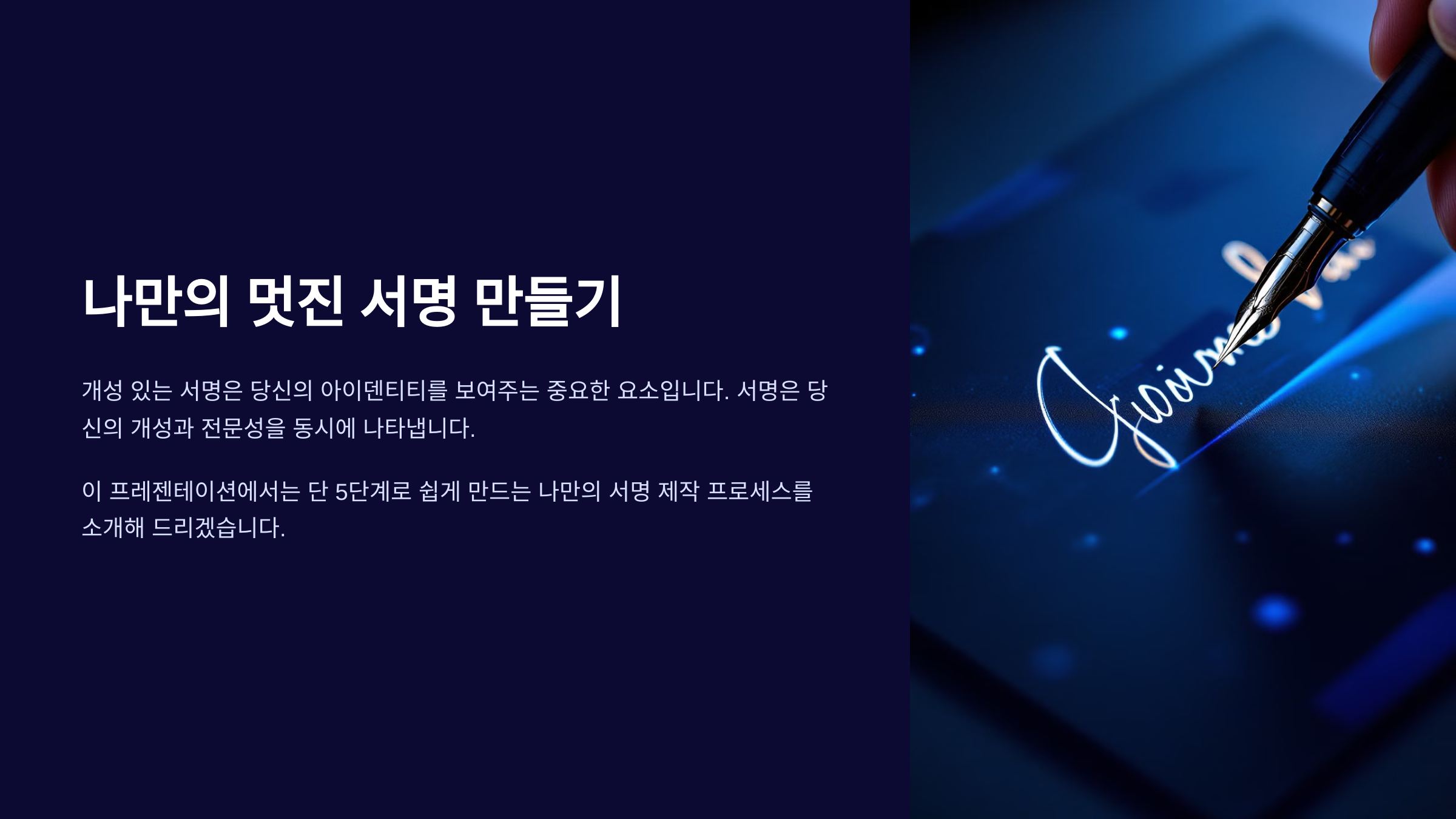
싸인을 바꾸는 과정은 단순한 글씨 연습이 아니라, 자신만의 개성과 스타일을 찾는 과정이기도 해요. 내가 생각했을 때, 싸인은 나를 표현하는 중요한 요소 중 하나예요. 그러니 단순히 멋있어 보이는 싸인을 따라 하기보다, 나에게 어울리는 싸인을 찾고 다듬는 것이 중요하답니다. 자, 이제 본격적으로 시작해 볼까요? ✨
1단계: 현재 싸인 분석하기 🔍
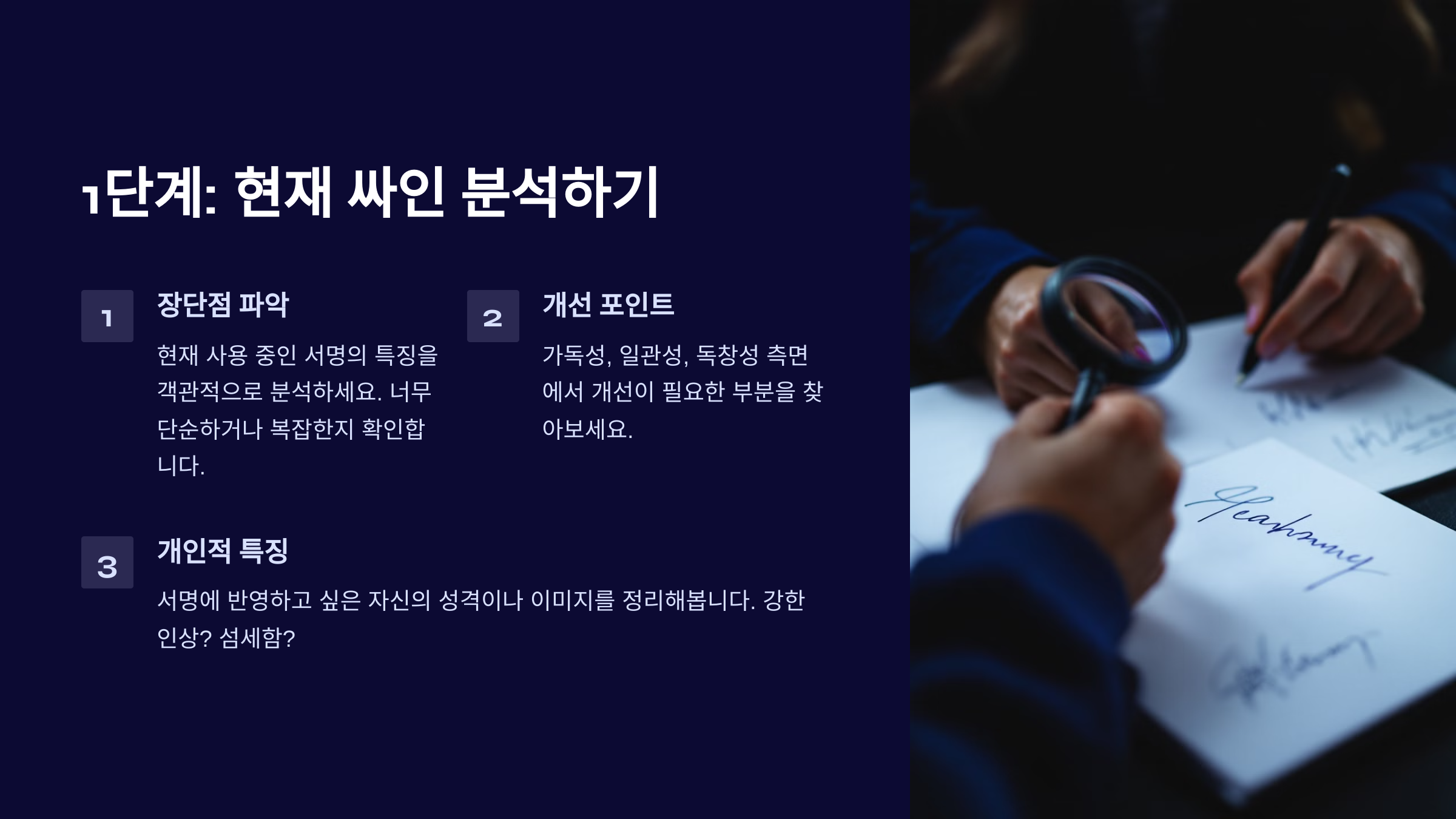
먼저, 현재 사용하고 있는 싸인을 분석하는 것이 중요해요. 어떤 점이 마음에 들고, 어떤 부분을 개선하고 싶은지 명확하게 파악하는 과정이 필요하죠. 싸인의 크기, 글자의 연결 방식, 가독성 등을 체크하면서 개선할 부분을 찾으면 좋아요. ✏️
📌 자신의 싸인을 분석하는 방법:
- 현재 싸인을 여러 번 써보고, 어떤 부분이 자연스럽고 어떤 부분이 어색한지 확인해요.
- 서명이 너무 크거나 작지는 않은지 체크해요.
- 읽기 쉬운 싸인인지, 아니면 너무 복잡한지 고민해봐요.
- 빠르게 쓸 때도 형태가 유지되는지 테스트해요.
✏️ 싸인의 주요 요소 분석 🧐
요소 분석 포인트 가독성 이름이 명확하게 보이는지? 연결 방식 글자들이 자연스럽게 연결되는지? 스타일 너무 평범하거나, 과하게 복잡하지 않은지? 속도 빠르게 써도 유지될 수 있는 디자인인지? 이렇게 싸인의 기본 요소를 점검한 후, 개선하고 싶은 포인트를 정리해요. 다음 단계에서는 어떤 스타일의 싸인이 나에게 잘 맞을지 찾아볼 거예요! 🔎
2단계: 원하는 스타일 찾기 🎨
이제 싸인을 더 세련되게 만들기 위해 나만의 스타일을 찾아야 해요. 싸인은 단순한 서명이 아니라, 개성과 감각을 담을 수 있는 작은 예술 작품이 될 수도 있답니다. 원하는 스타일을 찾기 위해 여러 가지 예시를 살펴보면서 자신의 이름과 조합해 보는 것이 중요해요. 🖊️
📌 대표적인 싸인 스타일 유형:
- 🖋️ 클래식 스타일: 정갈하고 읽기 쉬운 서명 (예: 정자체, 부드러운 곡선)
- ⚡ 모던 스타일: 빠르게 쓸 수 있도록 단순하면서도 감각적인 디자인
- ✨ 예술적 스타일: 독특한 필기체와 곡선을 강조한 서명
- 🔗 이니셜 스타일: 이름의 첫 글자만 강조해서 빠르고 강렬한 인상을 남김
📌 싸인 스타일 비교표 🖋️
스타일 특징 추천 대상 클래식 스타일 정갈하고 가독성이 좋은 서명 공식 문서, 계약서 서명에 적합 모던 스타일 단순하면서도 세련된 디자인 디자이너, 창작 활동을 하는 사람 예술적 스타일 곡선과 독특한 필기체 활용 예술가, 연예인, 크리에이터 이니셜 스타일 이름의 첫 글자만 강조 비즈니스 리더, 공인 자신의 이름을 여러 스타일로 써보면서 어떤 스타일이 가장 어울리는지 확인해 보세요. 싸인을 직접 연습하면서 자연스럽게 손에 익히는 것도 중요해요. 🎨
3단계: 기본 형태 디자인하기 ✏️
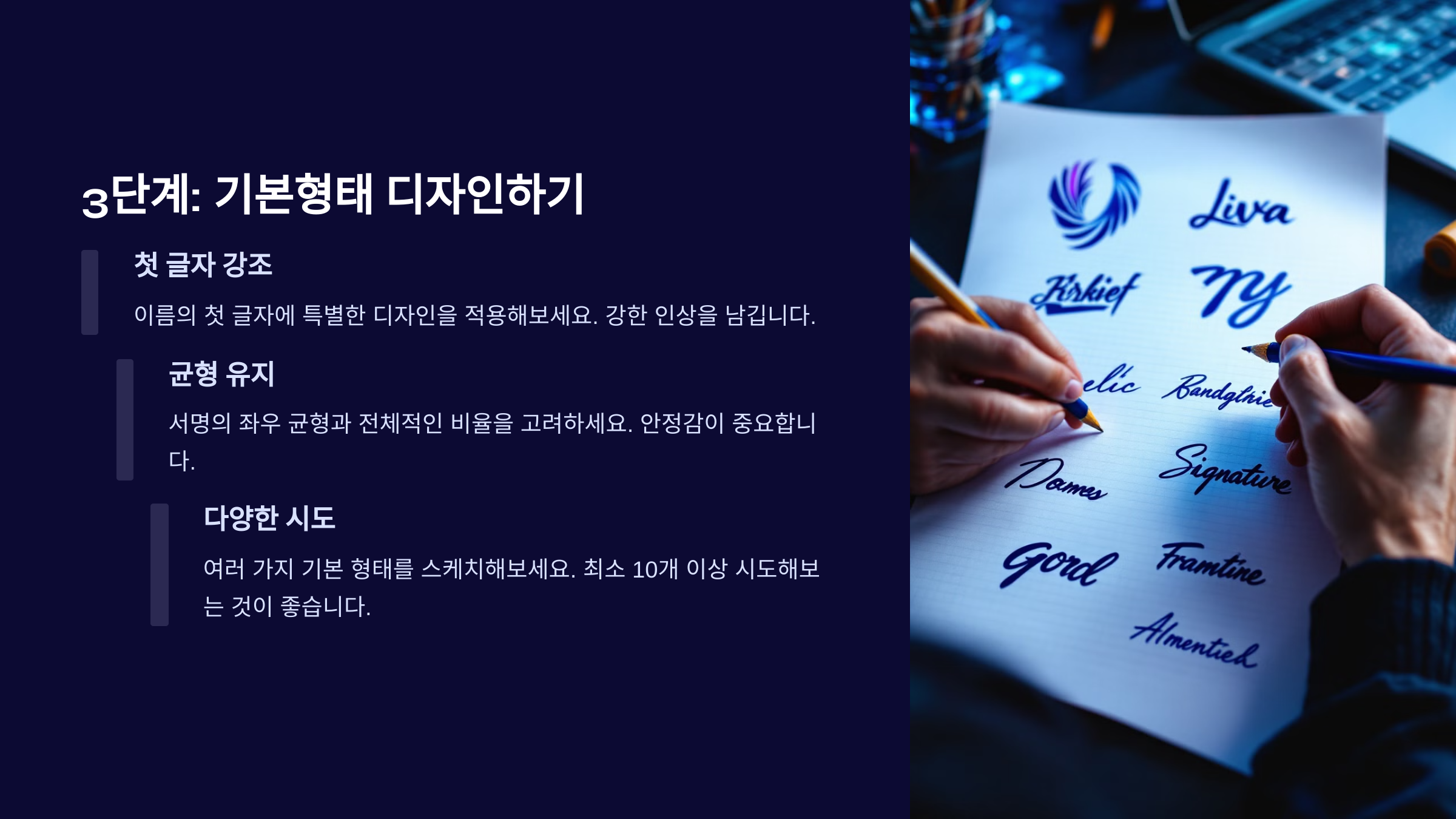
이제 원하는 스타일을 정했다면, 본격적으로 싸인의 기본 형태를 디자인할 차례예요. 싸인은 빠르게 쓰면서도 일관된 형태를 유지해야 하기 때문에, 단순하면서도 균형 잡힌 디자인을 만드는 것이 중요해요. 먼저 기본적인 형태를 잡고, 이를 반복적으로 연습하면서 자연스럽게 손에 익히는 과정이 필요하답니다. 🖋️
📌 싸인의 기본 형태를 만드는 3가지 핵심 요소:
- 🔤 이름의 전체 또는 일부를 활용하기: 풀네임을 쓰거나 이니셜을 조합하는 방식
- 🔄 자연스러운 흐름 만들기: 글자가 부드럽게 연결되도록 디자인
- ⚖️ 균형과 비율 맞추기: 싸인의 크기와 기울기를 일정하게 유지
✍ 기본 형태 디자인 방식 🏗️
디자인 방식 설명 풀네임 스타일 이름 전체를 활용하여 가독성을 높임 이니셜 스타일 이름의 첫 글자나 약어를 사용하여 빠르고 간결한 싸인 곡선 스타일 부드러운 곡선을 활용하여 세련된 느낌 강조 각진 스타일 직선과 각을 살려 강렬한 인상을 줌 여러 가지 스타일을 시도해 보면서 자신에게 가장 자연스럽고 멋진 싸인 형태를 찾아보세요! 기본 틀이 정해지면, 이제 세련된 디테일을 추가하는 과정으로 넘어갈 거예요. ✨
4단계: 세련된 디테일 추가하기 ✨
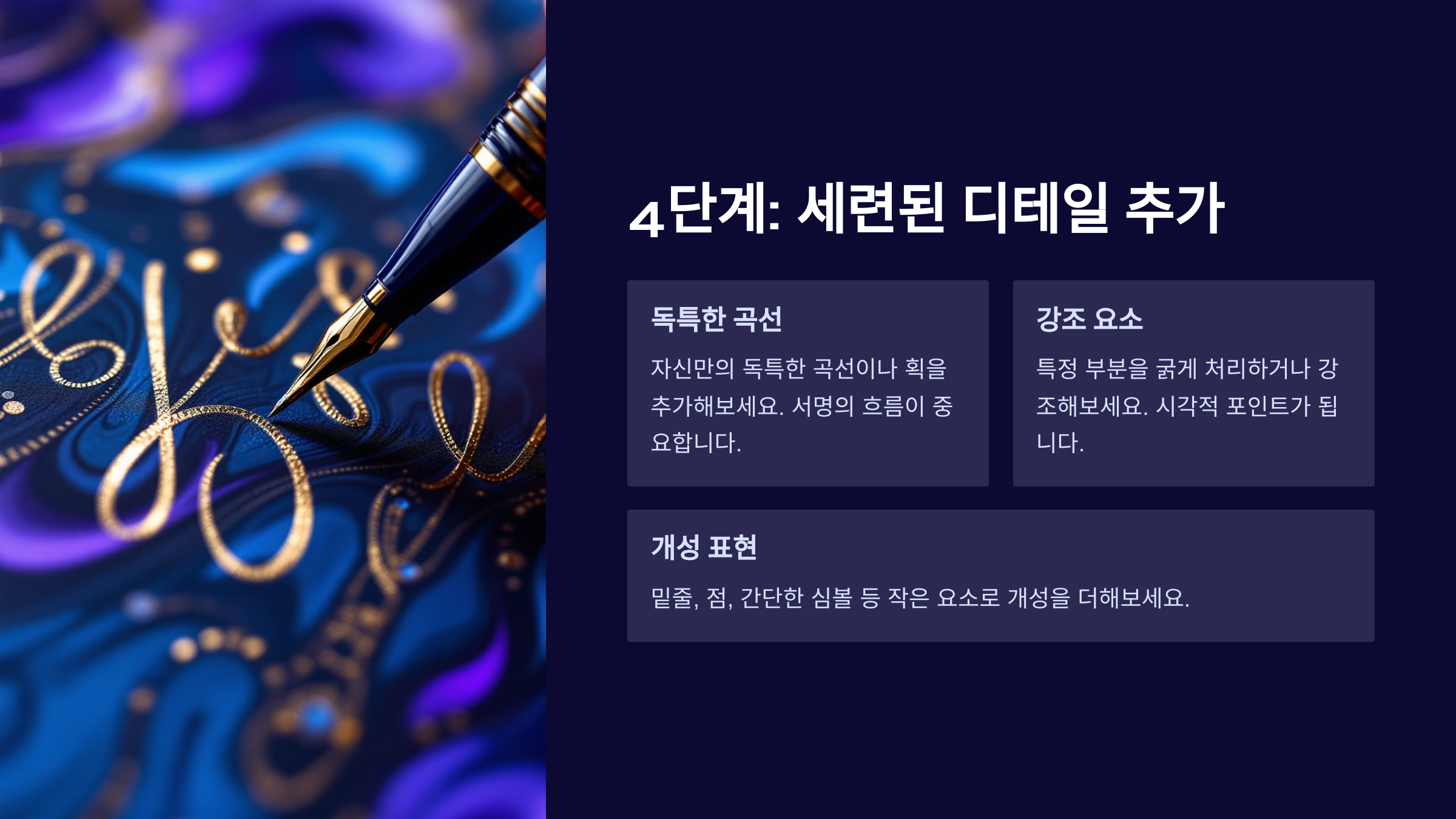
기본적인 싸인 형태가 완성됐다면, 이제 세련된 느낌을 더할 차례예요! 싸인을 멋있게 보이게 하는 핵심 요소는 작은 디테일이에요. 곡선, 점, 밑줄, 장식적인 요소를 적절하게 활용하면 더욱 개성 있고 스타일리시한 싸인을 만들 수 있답니다. 🖊️
📌 세련된 싸인을 만드는 디테일 요소:
- 〰️ 곡선: 부드러운 흐름을 만들어 고급스럽고 자연스러운 느낌을 줌
- 🖍️ 밑줄: 싸인을 강조하고 강한 인상을 남기는 효과
- ⚡ 점이나 짧은 선: 싸인에 개성을 더하는 작은 포인트
- 🔗 글자 연결 방식: 자연스럽게 이어지는 필기체 스타일 추가
🎨 세련된 디테일 추가 방법 🖋️
디테일 요소 효과 추천 스타일 곡선 자연스럽고 부드러운 느낌을 줌 예술적 스타일, 모던 스타일 밑줄 싸인을 강조하고 강렬한 인상을 남김 클래식 스타일, 이니셜 스타일 점이나 짧은 선 독특하고 개성 있는 느낌 추가 모던 스타일, 예술적 스타일 글자 연결 방식 빠르고 세련된 인상을 줌 모든 스타일에 적용 가능 이제 싸인이 더욱 개성 있고 세련된 모습으로 변했을 거예요! 하지만 싸인은 연습이 중요하죠. 이제 마지막 단계로, 싸인을 손에 익히고 실전에서 자연스럽게 활용하는 방법을 알아볼까요? 😊
5단계: 연습과 실전 적용 🏆
이제 완성된 싸인을 손에 익히고 실전에서 자연스럽게 활용하는 단계예요. 아무리 멋진 싸인을 만들어도 익숙하지 않으면 실제로 쓸 때 어색하거나 시간이 오래 걸릴 수 있어요. 연습을 통해 싸인의 일관성을 유지하고, 자연스럽게 사용할 수 있도록 훈련하는 것이 중요해요. 🖊️
📌 효과적인 싸인 연습 방법:
- 📄 종이에 반복해서 써보기: 빈 종이에 같은 싸인을 여러 번 써서 손에 익히기
- ⏳ 속도 테스트하기: 빠르게 싸인을 해도 균형이 유지되는지 체크
- 📝 다양한 환경에서 연습: 펜, 볼펜, 연필 등 다양한 필기구로 연습
- ✍️ 실제 서류에 적용: 계약서, 영수증, 카드 서명 등에 직접 사용해 보기
🎯 싸인 연습 체크리스트 ✅
연습 목표 체크 여부 ✔ 싸인의 일관성이 유지됨 ⬜ 빠르게 써도 균형이 맞음 ⬜ 다양한 필기구로 테스트함 ⬜ 실제 문서에서 활용해봄 ⬜ 꾸준히 연습하면 자연스럽고 세련된 싸인을 자유롭게 사용할 수 있을 거예요! 이제 자신만의 멋진 싸인으로 자신감을 더해보세요. 😊
Q1. 싸인을 바꿔도 법적으로 문제가 없나요?
A1. 네! 다만, 공식 문서에 등록된 싸인과 다르면 혼란이 생길 수 있으니 신분증, 은행 서류 등에 사용하는 싸인은 유지하는 것이 좋아요.
Q2. 싸인을 쉽게 만들 수 있는 방법이 있을까요?
A2. 이름의 이니셜을 활용하거나, 필기체를 참고하여 자연스러운 흐름을 만들면 쉽게 디자인할 수 있어요.
Q3. 유명인의 싸인을 따라 해도 되나요?
A3. 참고는 가능하지만, 자신의 개성을 담아 고유한 싸인을 만드는 것이 더 좋아요.
Q4. 싸인을 너무 복잡하게 하면 안 좋은가요?
A4. 네, 너무 복잡하면 빠르게 쓰기 어렵고 실용성이 떨어질 수 있어요. 단순하면서도 개성이 드러나는 디자인이 가장 좋아요.
Q5. 필기체를 잘 못 쓰는데 괜찮을까요?
A5. 필기체가 꼭 필요하지 않아요! 직선적이거나 심플한 디자인도 충분히 멋진 싸인이 될 수 있어요.
Q6. 싸인 연습을 얼마나 해야 하나요?
A6. 하루 10~15분씩 연습하면 빠르게 손에 익힐 수 있어요. 꾸준히 반복하는 것이 중요해요.
Q7. 싸인을 디지털로 만들어도 되나요?
A7. 네! 디지털 서명도 많이 사용되므로 전자 서명 앱을 활용해 만들 수도 있어요.
Q8. 싸인을 너무 자주 바꾸면 안 되나요?
A8. 중요한 문서에 사용된 싸인은 변경이 어렵지만, 개인적으로 사용하는 싸인은 원하는 대로 바꿀 수 있어요.
🔥 싸인 완성! 이제 멋지고 세련된 싸인으로 자신감을 더해보세요!